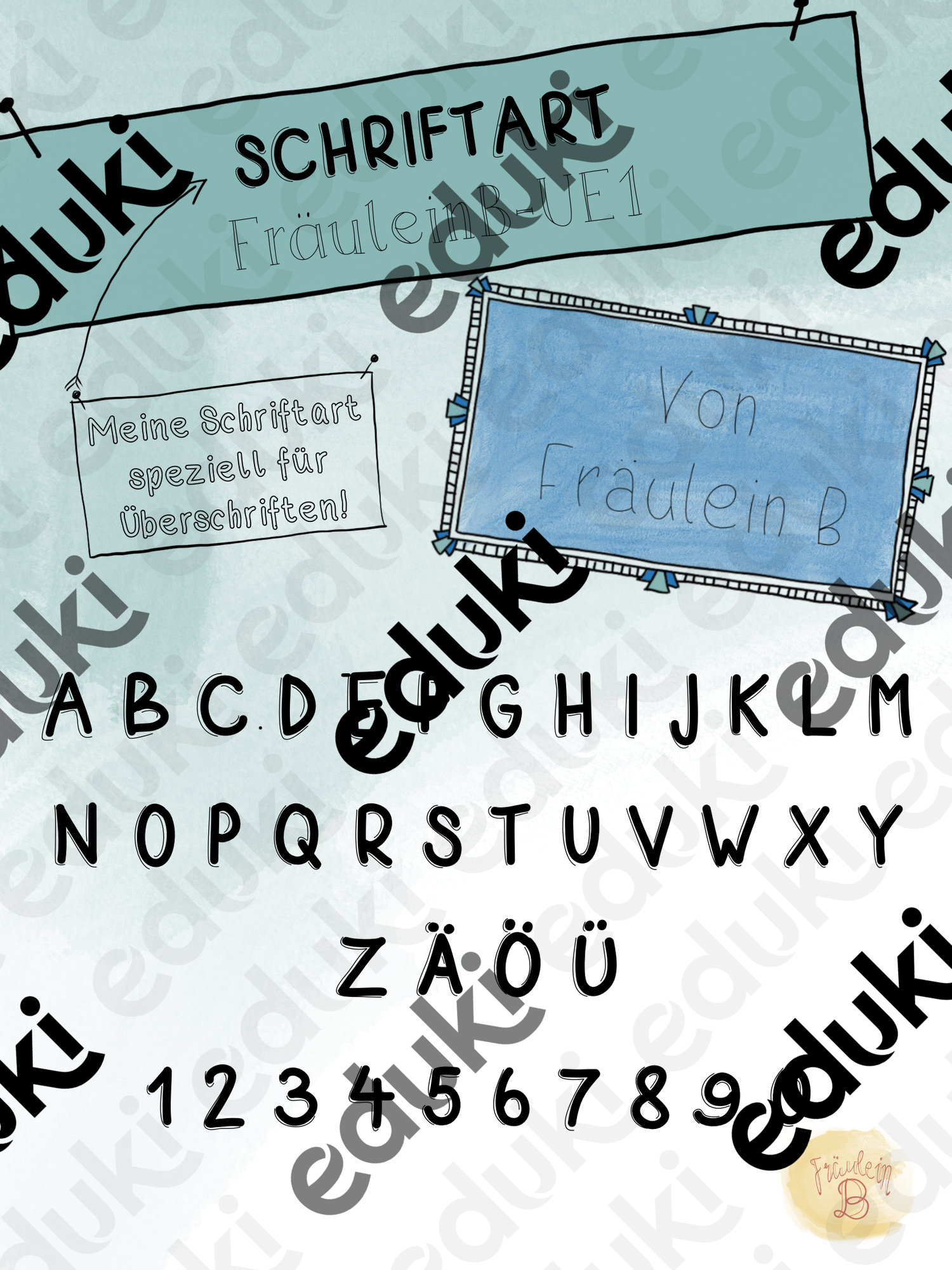
selbst erstellte Schriftarten - Schriftart "FräuleinB-Ue1" - speziell für Überschriften - Fräulein B - Deckblatt
anbei findest du eine Schrift von mir, welche ich speziell für Überschriften verwende.
Schriftart "FräuleinB-Ue1" - speziell für Überschriften